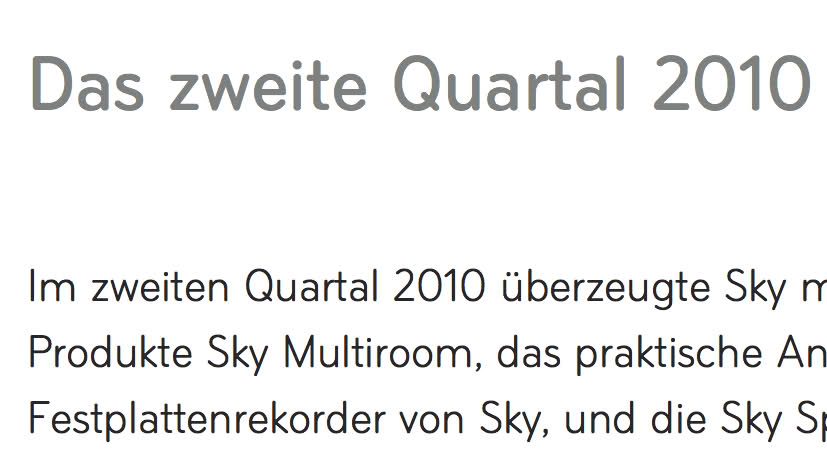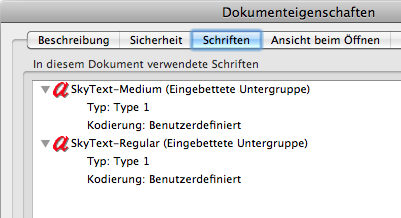
ich würde gerne wissen, welche Schriftart Sky benutzt. Ich dachte es ist VAG Rounded, aber irgendwie ist doch eine Abweichung zu dieser Schrift vorhanden. Wurde die Schrift evtl. für Sky geändert oder ist es eine andere?
"Sky Text" heißt die gute.
Keine Ahnung, ich hab nur ins Quartalsberichts-pdf reingeschaut. Kann ich mir aber nicht vorstellen, dass sie, nur weil sie rund ist, auf der VAG aufbaut.